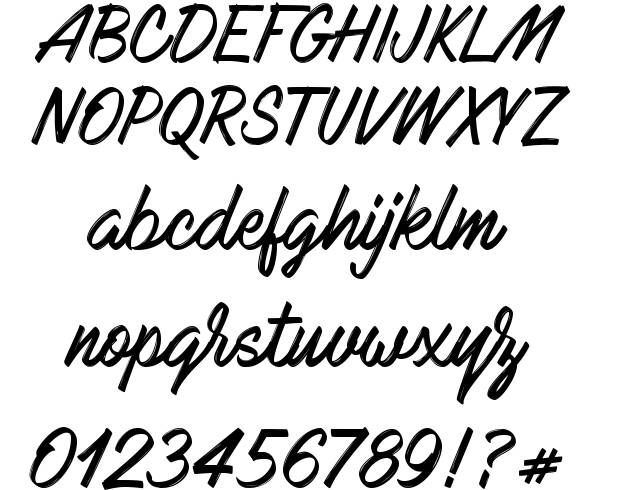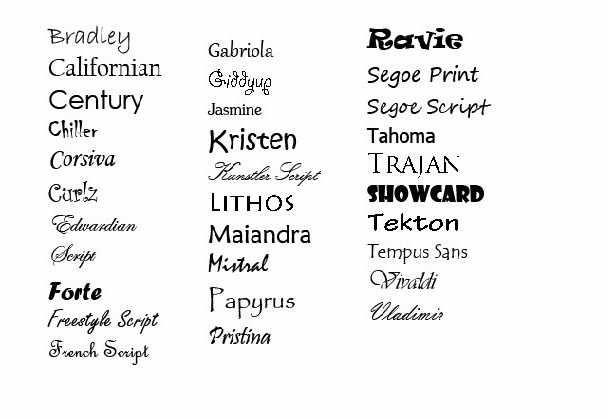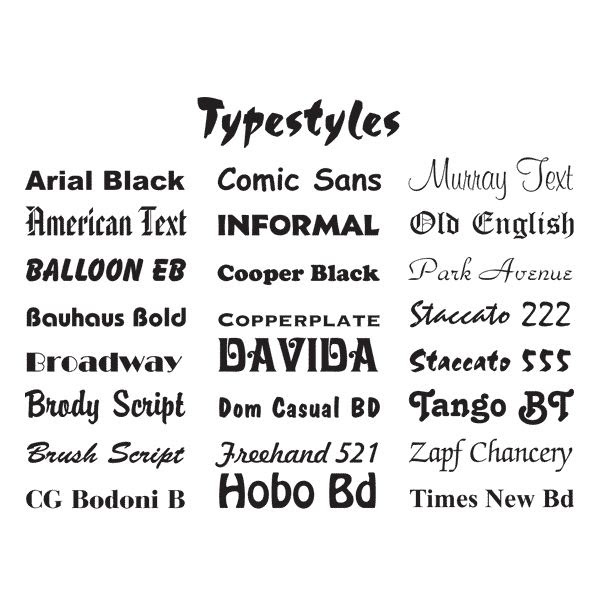
Как сделать красивый шрифт в Word?
Что в операционной системе Windows, что текстовом редакторе Word (это тот, который входит в пакет программ MS Office) используется один и тот же набор шрифтов. Для оформления большинства документов его как то хватает. Но если вам захочется сделать что то уникальное, что то особенно красивое, то с выбором шрифта появятся затруднения.
Для создания красивого шрифта, вам потребуется наличие интернета, чтоб скачать его и поставить на свой компьютер. После чего, вы спокойно сможете начать красиво оформлять документы. Давайте по шагам рассмотрим процесс под названием «как сделать красивый шрифт в ворд».
Очень удобно для человека который ищет красивый шрифт вводить интересующую фразу в поиске на сайте где вы ищите красивый шрифт. Также есть оценки от других пользователей, что может повлиять на ваш выбор. Хотелось бы еще напомнить о том, что не все шрифты предлагаются как для русской так и английской раскладки клавиатуры. Это напоминание важно, если в тексте вы будете использовать английский буквы.
И в дополнении ко всему хочу напомнить о том, что вкусы у всех разные. Надо быть аккуратным при выборе шрифта в Word. Да и самом предназначение программы — это создание деловых документов которые хорошо читаются.
Изменение цвета шрифта: Нажмите кнопку «Цвет текста», затем выберите цвет в окне «Цвета».
См. раздел Использование цветов в документах.Подчеркивание или зачеркивание текста. Нажмите кнопку «Подчеркнуть текст» или «Зачеркнуть текст», затем выберите параметр во всплывающем меню, например «Две линии». Чтобы изменить цвет линии, выберите во всплывающем меню пункт «Цвет», затем выберите цвет.
Вставка символов и букв: Откройте меню действий, выберите пункт «Символы» и перетяните символ из приложения «Символы» в свой документ.
Настройка параметров оформления: Откройте всплывающее меню действий и выберите «Оформление». Если выбранный шрифт поддерживает возможности оформления, выберите или отмените выбор параметров.
Для установки шрифтов на компьютер Mac и управления ими используйте приложение «Шрифты». Чтобы открыть ее из окна «Шрифты», нажмите меню действий и выберите «Управление шрифтами». См. Руководство пользователя приложения «Шрифты».
Чтобы преобразовать буквы в выбранном тексте в верхний, нижний или смешанный регистр, выберите «Правка» > «Преобразования», затем выберите вариант.
Архитектурный шрифт для Word: установка
Для различных документаций и спецификаций требуется особый вид шрифтов. Обычно это устанавливается ГОСТом, то есть текст должен писаться исключительно по правилам. Написание по ГОСТу регламентируется специальным документом, в котором прописаны параметры шрифта. Так, например, для чертежей используется определенный государственный стандарт, который конкретно задает размер текста. В архитектурных чертежах применяются свои правила написания текста, которые отличаются тем, что буквы несколько уже, чем в обычных чертежах. Архитектурный шрифт несколько проще, чем чертежный, так как здесь нет наклона текста.